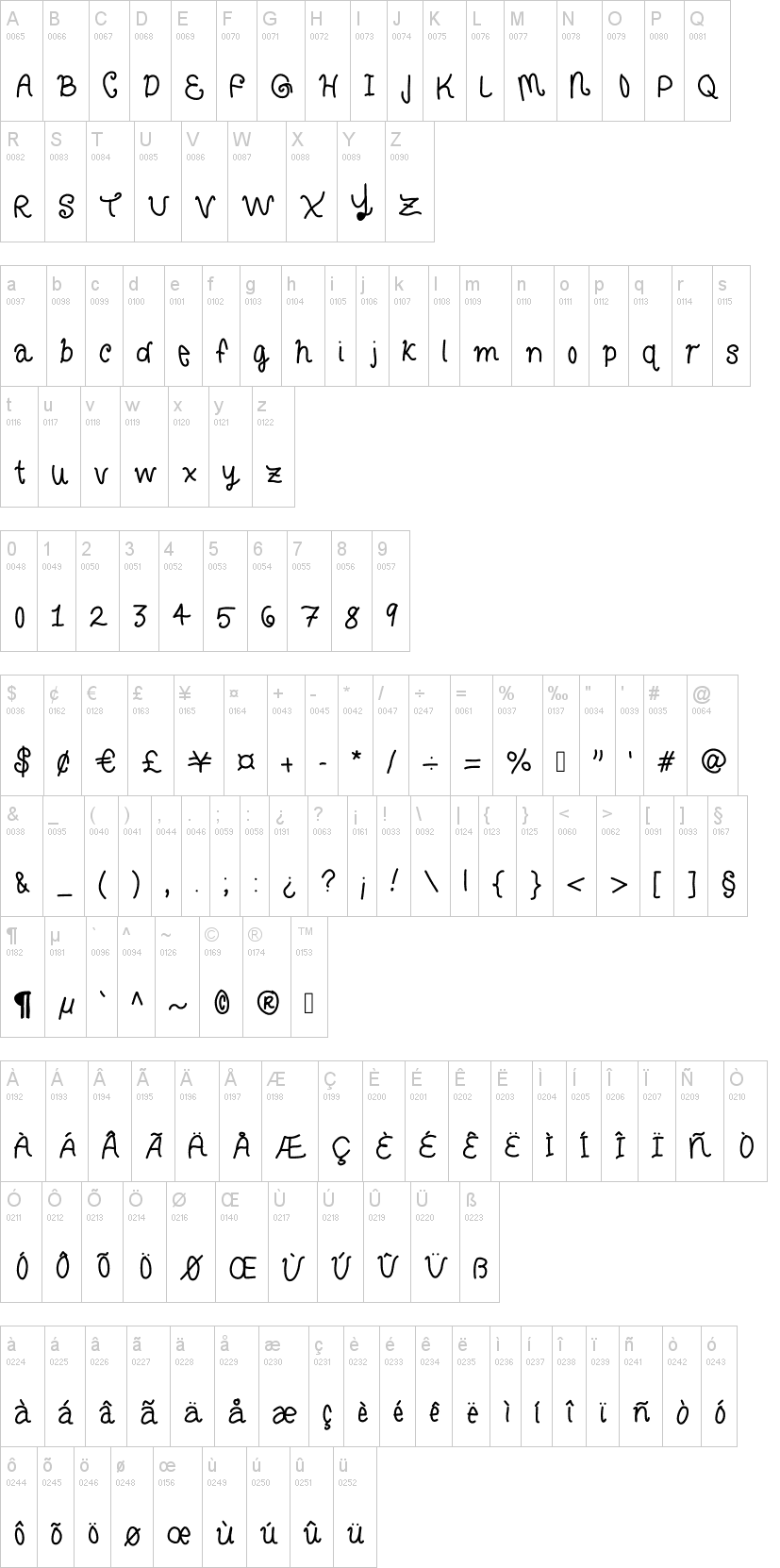
? Curly Letters 字体是一款手写风格的字体,它具有温暖、柔和、活泼的特点,适用于各种设计项目,尤其是用于制作节日卡片、婚礼邀请函、海报、招贴、标识等。它的文字有着旋转的曲线,让人感受到温暖、舒适的氛围,更能够更好地表现出文字的韵律感。内容介绍
Curly Letters是一款非常不错的手写艺术字体,具有很好的视觉感,适合于文化类的宣传设计、商业类品牌的广告和产品包装设计以及个性化文字排版等较多场景。